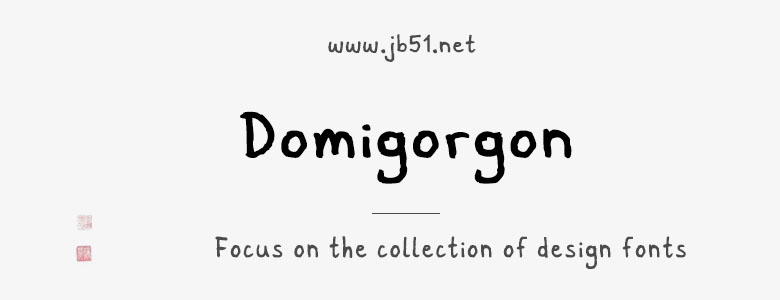
Domigorgon英文手寫(xiě)字體,字體筆觸略粗,書(shū)寫(xiě)流暢,具有很好的視覺(jué)感,適合應(yīng)用于藝術(shù)設(shè)計(jì)、平面宣傳設(shè)計(jì)、網(wǎng)頁(yè)設(shè)計(jì),書(shū)法字帖等領(lǐng)域。有需要的朋友快來(lái)本站下載使用吧。